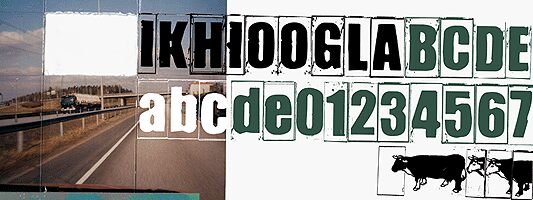
IKHIOOGLA 3 von Junkohanhero ist eine kostenlose, distressed Display-Schriftart mit einem rauen, plakativen Charakter. Die Buchstaben wirken wie massive Blockformen in abgenutzten Rahmen – mit abgeblätterten Kanten, unebenen Ausbrüchen und einer handgemachten Körnung, die eher an Xerox-Punk und Street-Flyer erinnert als an polierte digitale Typografie.
Damit ist diese kostenlose Schrift die ideale Wahl für Gig-Poster, Zine-Cover, Plattencover, Titel und kurzes Branding, bei dem die Box-Buchstaben fast wie gestempelte Etiketten wirken. Sie funktioniert am besten, wenn man die Textur für sich sprechen lässt – in kompakten Überschriften, rohen Monogrammen oder kurzen Coverzeilen, die einen ramponierten, improvisierten Look brauchen.